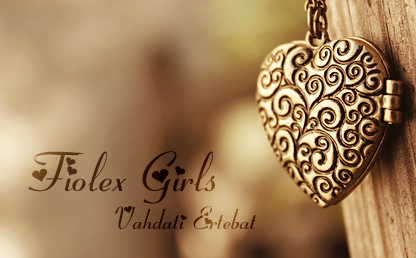
فونت Fiolex Girls یکی از فونتهای زیبا و فانتزی انگلیسی بوده که توسط Fiolex Home Studio طراحی شده است . شما میتوانید در طرحهای خود از این فونت زیبا استفاده نمایید . امیدوارم این فونت مورد پسند شما قرار بگیرد .